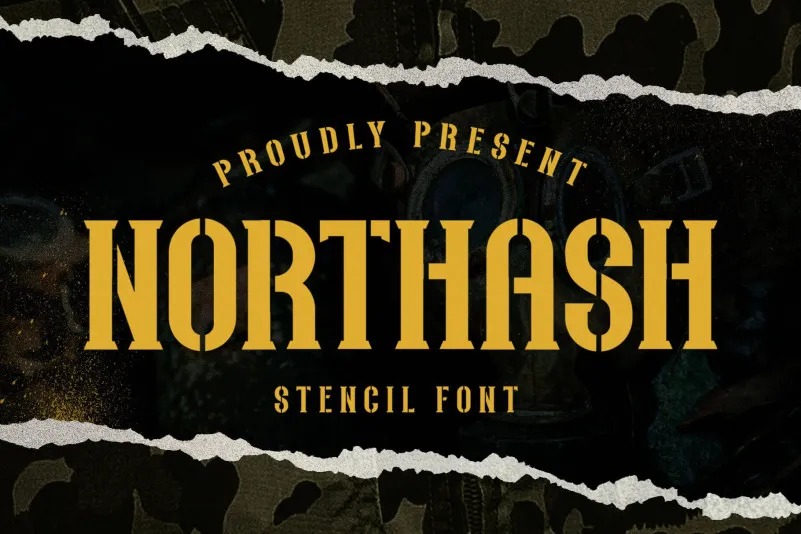
A Northash Font é uma elegante tipografia para fins visuais que se inspira nos estilos antigos dos sinais de trânsito e na arquitetura militar. Inspirada no vintage, ela transmite um estilo robusto e respeitável, perfeitamente adequado a vários temas como esportes, militares, cidade moderna ou urbana, fauna selvagem, e até mesmo o clima nostálgico de antiguidade. Seu layout da letra é um pouco apertado, criando uma aparência forte e digna que torna a Northash Font um recurso valioso para estilos dinâmicos e versáteis em projetos visuais. É perfeita para aqueles buscando uma fonte de texto com personalidade e estilo único que brilha ao contrário dos padrões convencionais.